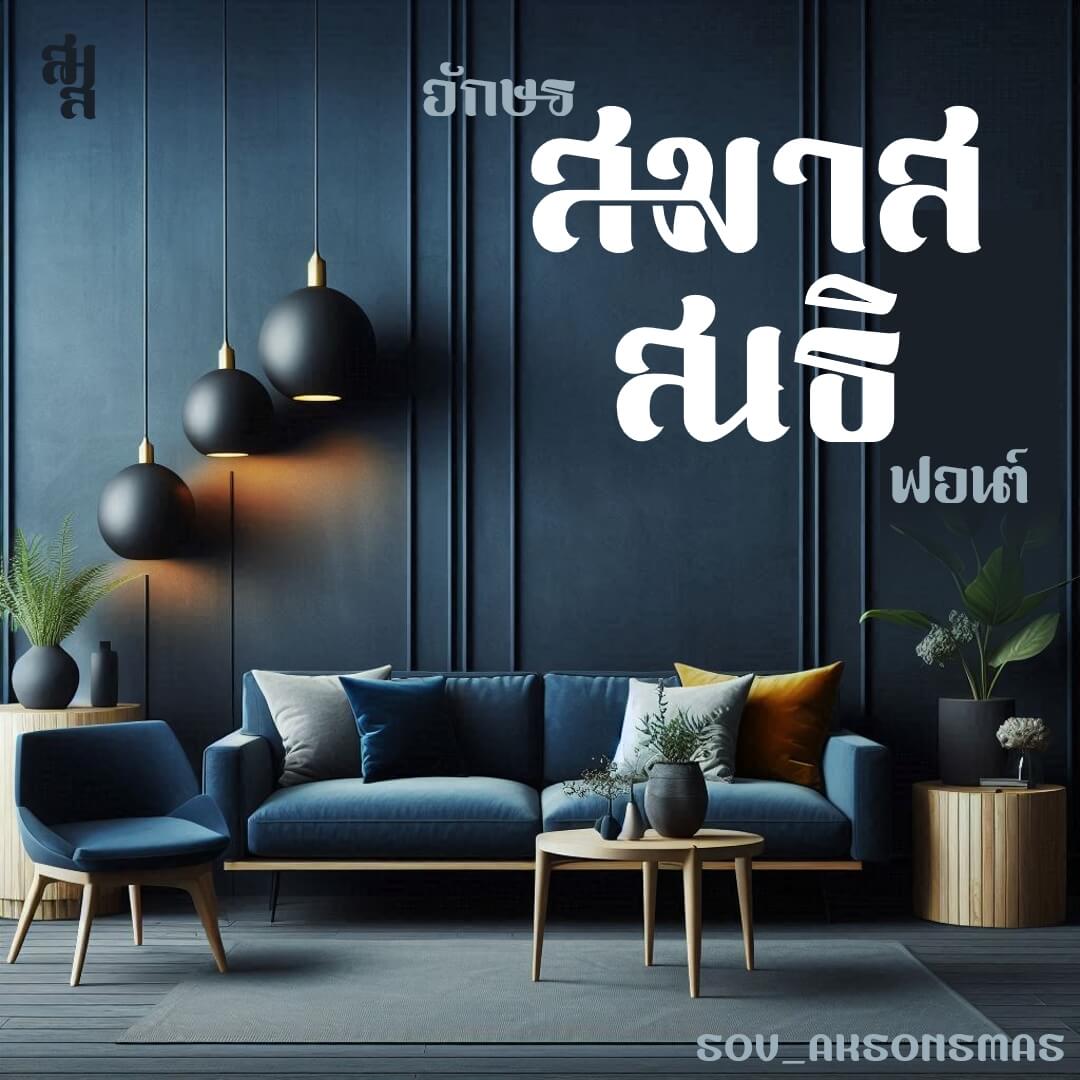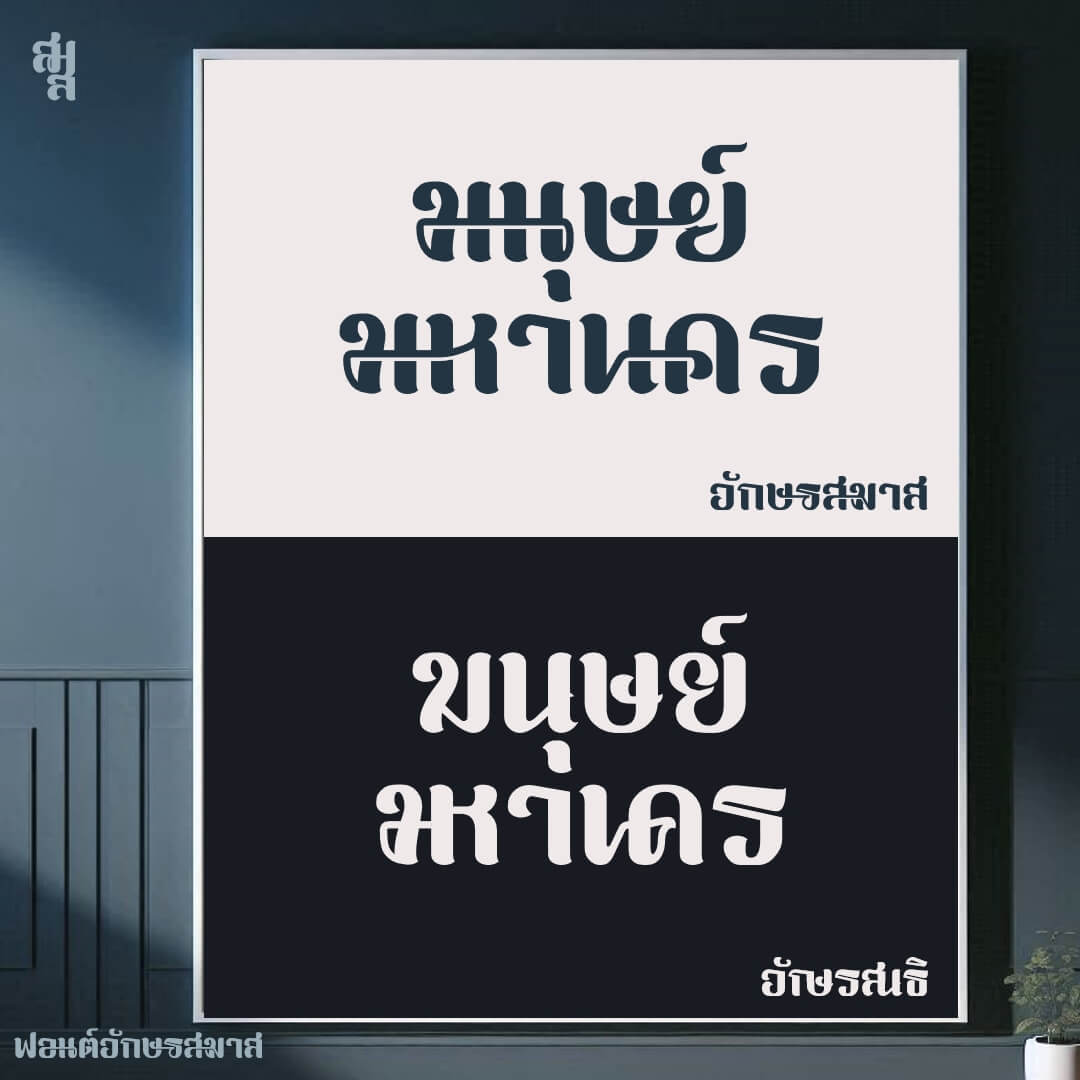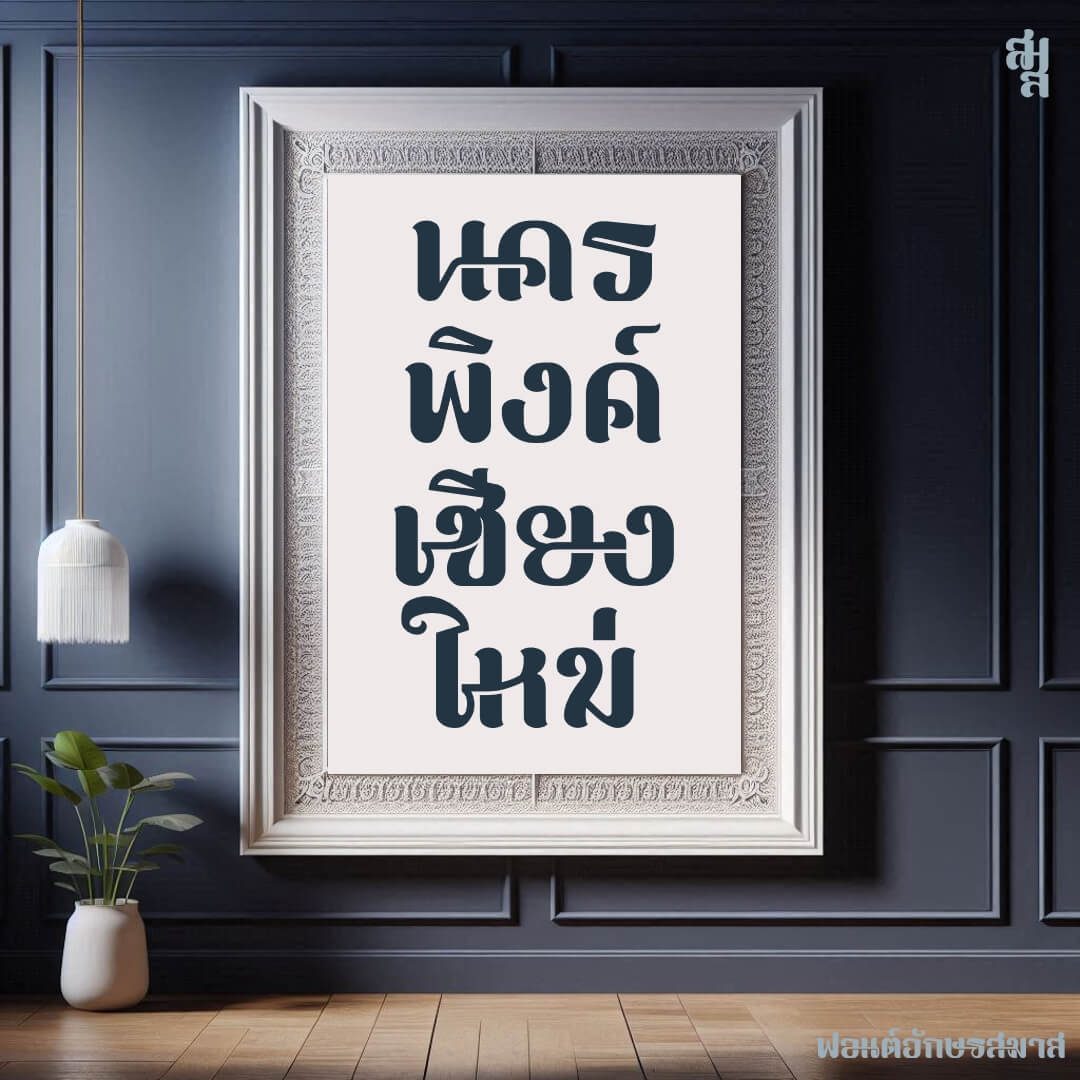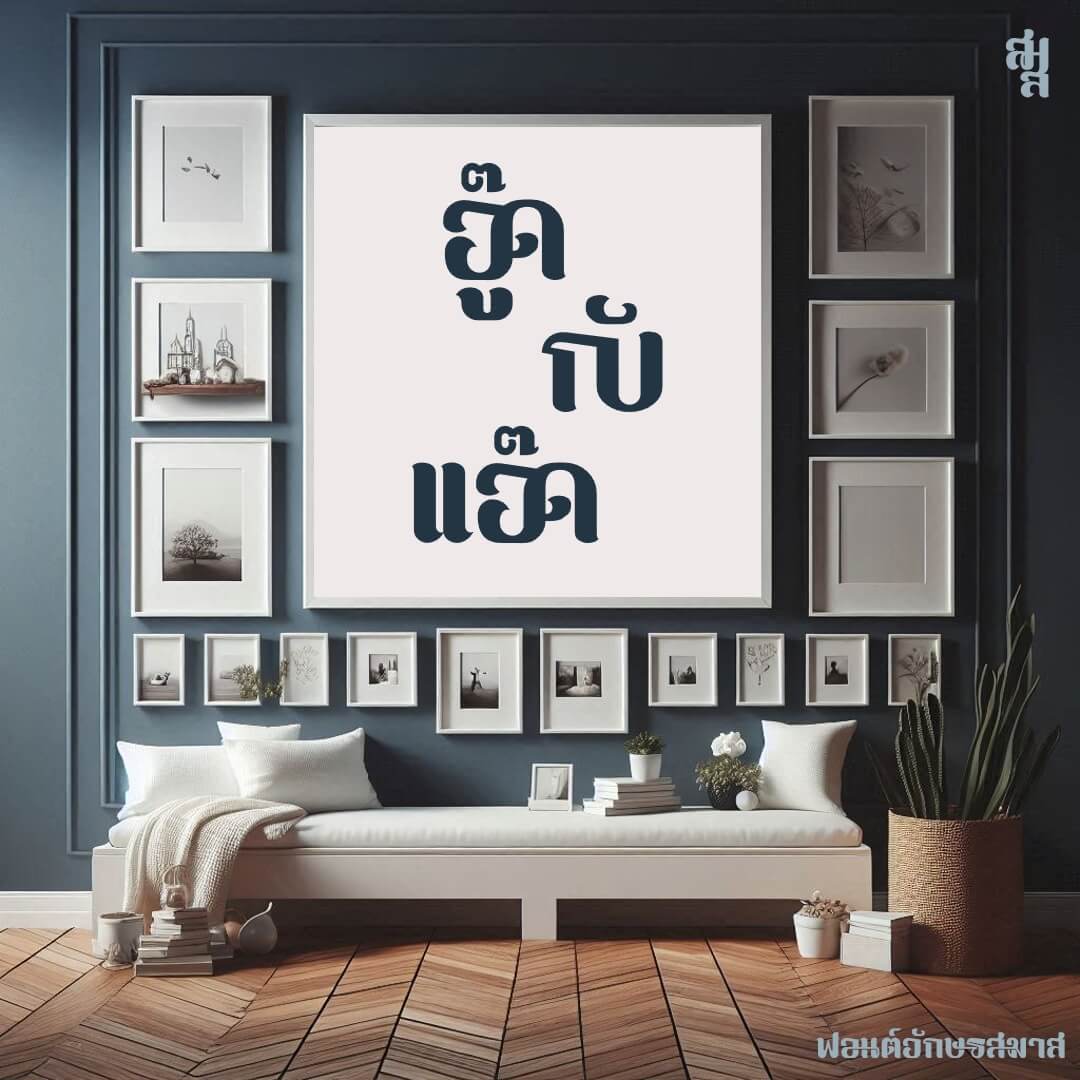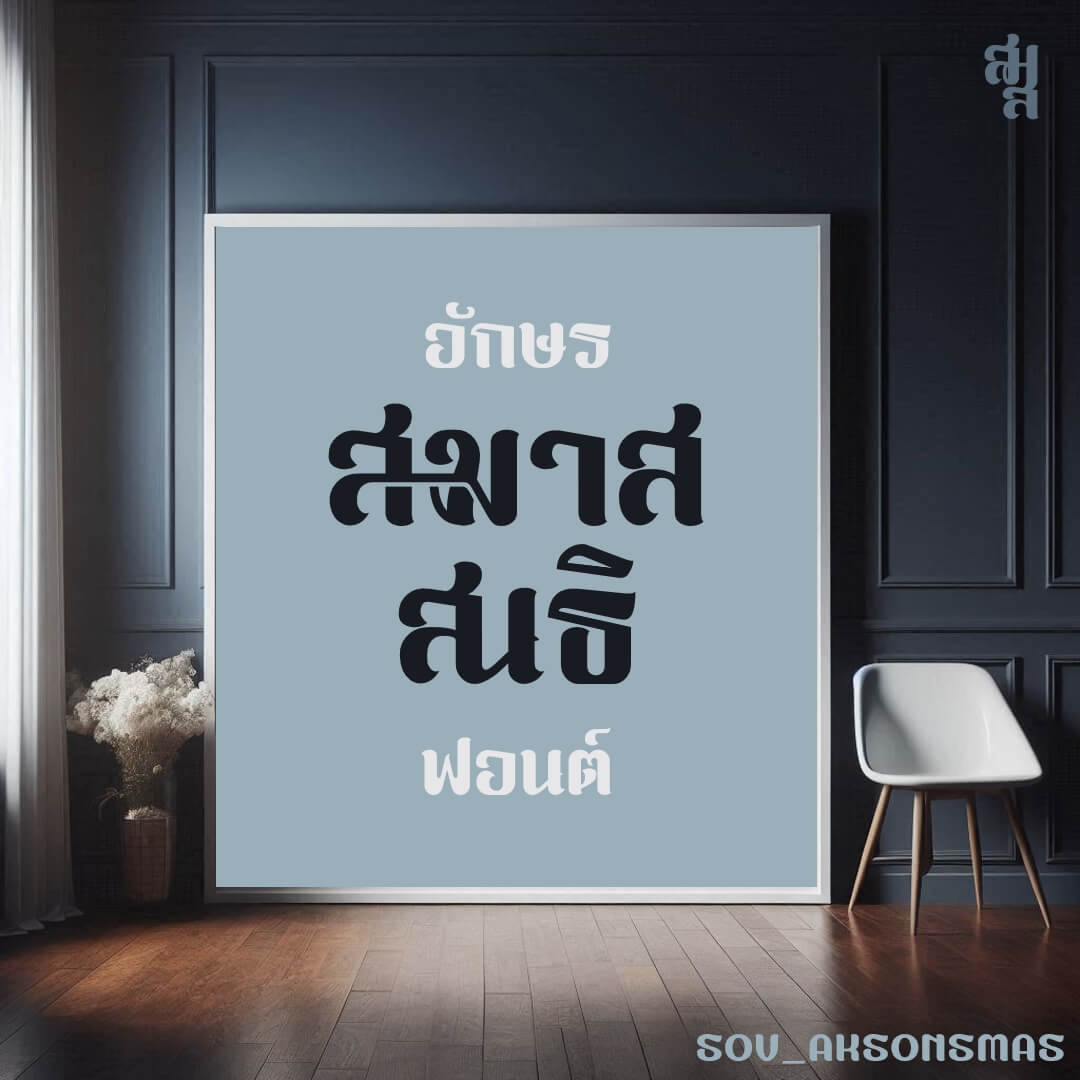
อักษรสมาส-สนธิ (SOV_AksonSmas)
ฟอนต์อักษรสมาส-สนธิ – แนวคิดจากคำสมาส คำสนธิ คือเอาตัวอักษรมาเชื่อมเส้นกันเฉยๆ หรือรวมร่างกันไปเลย… ตัวปรกติเป็นอักษรสมาส เชื่อมเส้น ถ้ากด bold จะกลายเป็นอักษรสนธิ ร่วมร่างกัน
ถ้าไม่ถูกใจคู่ไหน ให้กด ฯฯ แทรกกลางระหว่างเขา